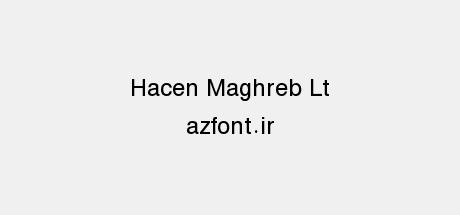
فونت زیبای رایگان Hacen Maghreb Lt
قلم زیبای Hacen Maghreb Lt از سری قلم های بسیار زیبا برای تایپوگرافی و لوگو تایپ می باشد.این قلم در وزن Regular و توسط Mohamed Hacen Mottaly طراحی و منتشر شده است.